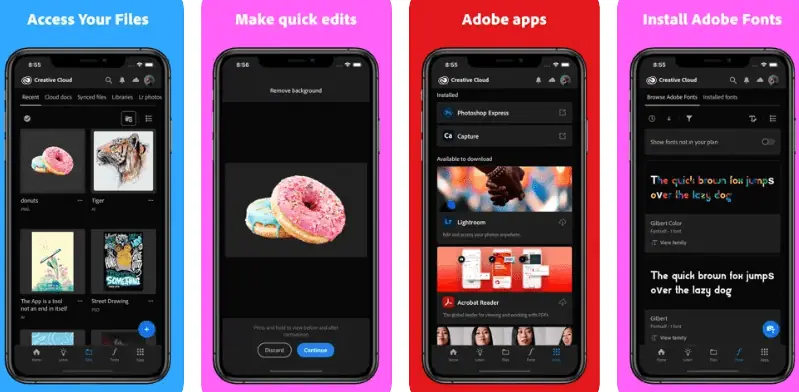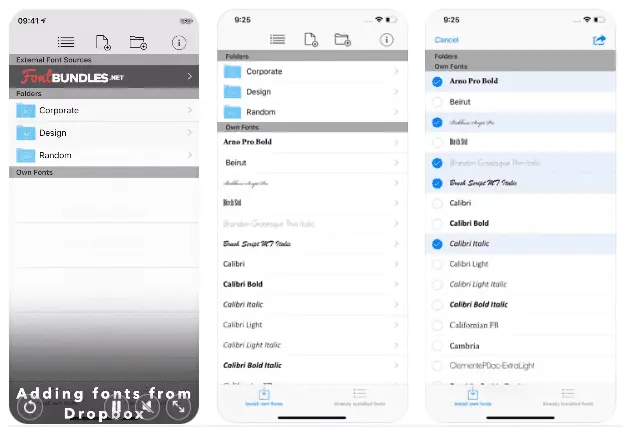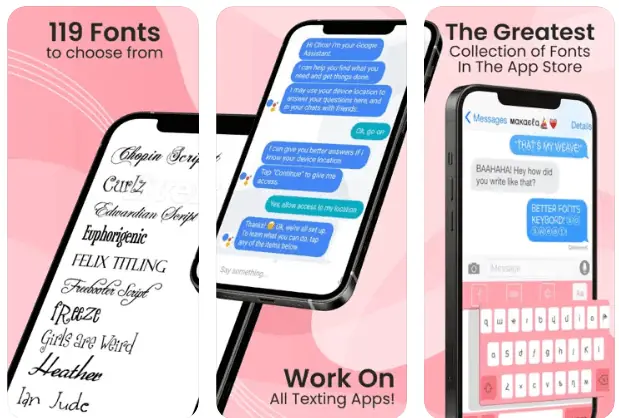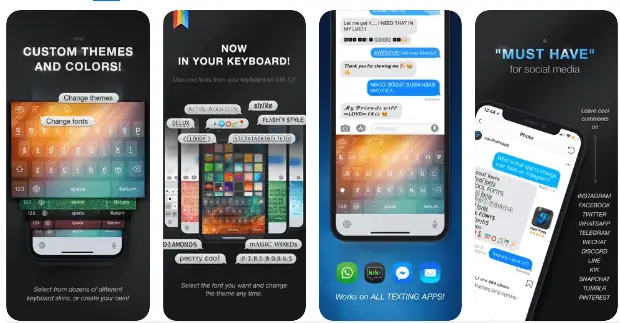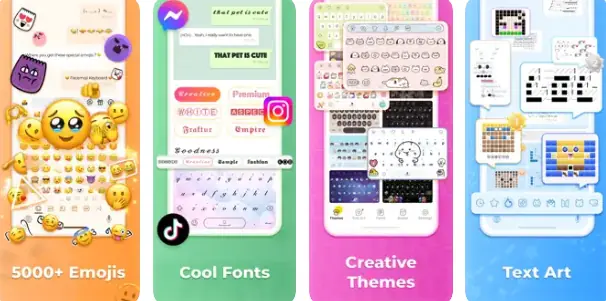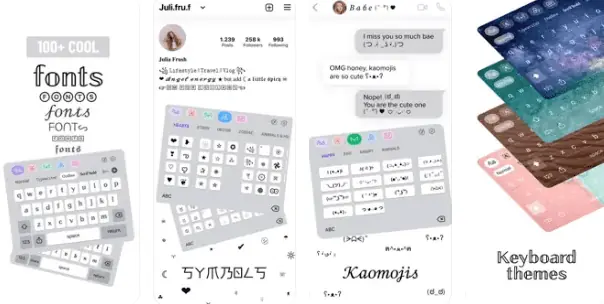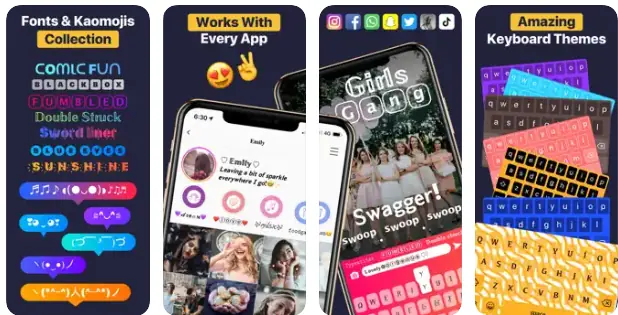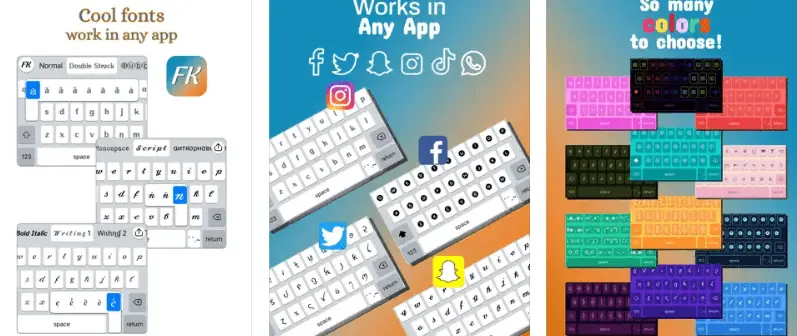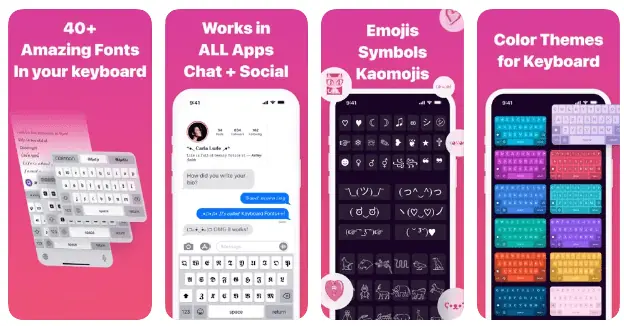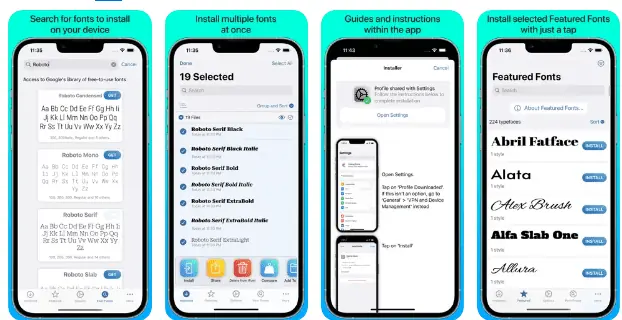
Die individuelle Gestaltung des eigenen Smartphones ist bei vielen sehr beliebt. Daher wollen wir uns einige der besten Apps für Schriftarten ansehen, mit denen du dein iPhone personalisieren kannst.
Viele Blogger haben angemerkt, dass iPhones in Bezug auf Individualisierung nicht ganz mit Android-Geräten mithalten können. Das mag bis zu einem gewissen Punkt stimmen, doch Apple hat stetig nachgebessert und steht dem Konkurrenten inzwischen in nichts nach.
Diese Entwicklung wird deutlich, wenn man sich die Vielzahl an Apps und Widgets im App Store anschaut, die es Nutzern ermöglichen, ihr Smartphone zu personalisieren. Dieser Artikel richtet sich an alle, die ihr Gerät gerne individuell gestalten möchten.
Personalisierung kann viele Aspekte umfassen, wie etwa Automatisierungen, das Hinzufügen von Kurzbefehlen oder Änderungen bei Bildschirmanimationen. Hier soll es um eine kleine, aber wirkungsvolle Anpassung gehen: die Schriftart deines iPhones. Lass uns also keine Zeit verlieren und direkt zu den Apps kommen!
Was sind Schriftarten-Apps?
Bevor wir uns den besten Schriftarten-Apps für iOS widmen, wollen wir kurz definieren, was Schriftarten-Apps eigentlich sind. Im App Store gibt es Millionen von Anwendungen, die unterschiedliche Funktionen erfüllen, und Schriftarten-Apps gehören auch dazu.
Mit Schriftarten-Apps können Nutzer den Stil der Schrift auf ihren Mobilgeräten verändern. Sie bieten eine vielfältige Auswahl an Fonts und Anpassungsmöglichkeiten. Es ist sogar möglich, die Schriftart in einer einzelnen App oder systemweit zu ändern.
Es gibt sowohl kostenlose als auch kostenpflichtige Schriftarten-Apps, wobei Premium-Fonts oft ausgefeiltere und individuellere Anpassungsmöglichkeiten bieten. Viele dieser Apps ermöglichen nicht nur die Veränderung von Größe und Farbe, sondern bieten auch zusätzliche Funktionen wie Texteffekte und Hintergründe.
Schriftarten-Apps können zwar eine unterhaltsame Möglichkeit sein, das Aussehen deines Smartphones zu verändern, aber es ist wichtig zu beachten, dass nicht alle Fonts mit allen Apps und Geräten kompatibel sind. Zudem sind manche Schriftarten möglicherweise nicht optimal in Bezug auf Lesbarkeit und Barrierefreiheit. Daher ist es wichtig, Schriftarten zu wählen, die gut lesbar und benutzerfreundlich sind. Vorsicht ist auch geboten, wenn Schriftarten von Drittanbieter-Webseiten bezogen werden, da diese Schadsoftware und andere Sicherheitsrisiken bergen können.
Warum sollte ich die Standardschriftart auf meinem iPhone ändern?
Wenn es um Schriftarten-Apps geht, stellt sich oft die Frage: Ist es wirklich nötig, die Standardschriftart zu ändern? Die einfache Antwort lautet: Nein.
Die Entscheidung, den Schriftstil und die -größe zu ändern, liegt ganz bei dir. Du hast aber sicher bemerkt, dass die Schriftart das Erscheinungsbild stark beeinflusst, egal ob es sich um ein Dokument, Instagram-Storys oder eine Biografie handelt. Viele verwenden unterschiedliche Schriftarten, um ihre Biografie oder Story attraktiver zu gestalten und hervorzuheben.
Zusammenfassend lässt sich sagen, dass ein Schriftartenwechsel nicht zwingend notwendig ist. Es ist aber dennoch eine Option, die das Erscheinungsbild und die Benutzerfreundlichkeit verbessern kann. Hier sind einige Vorteile, die eine Änderung der Standardschriftart mit sich bringen kann:
Verbesserte Lesbarkeit
Manche Schriftarten sind besser lesbar als andere, besonders für Menschen mit Sehbeeinträchtigungen. Durch die Anpassung der Standardschriftart kannst du eine auswählen, die für dich bequemer und leichter zu lesen ist.
Personalisierung
Eine andere Standardschriftart kann deinem iPhone eine persönliche Note verleihen. Du kannst einen Font wählen, der deinen Stil oder deine Persönlichkeit widerspiegelt oder einfach mal etwas Neues ausprobieren.
Barrierefreiheit
Das Ändern der Schriftart kann die Bedienung für Menschen mit Sehbehinderung oder Legasthenie erleichtern. Einige Schriftarten sind speziell so gestaltet, dass sie mit klareren, größeren Buchstaben und besseren Abständen zwischen Buchstaben und Wörtern leichter zugänglich sind.
Verbesserter Fokus
Manche Schriftarten sind angenehmer für das Auge als andere. Dies kann helfen, Augenbelastung zu reduzieren und deine Konzentrationsfähigkeit zu verbessern. Schriftarten wie Helvetica oder Arial werden oft als beruhigender und angenehmer empfunden als verspielte oder dekorative Schriftarten.
Bessere Produktivität
Eine leichter lesbare und weniger ablenkende Schriftart kann deine Produktivität und Effizienz bei der Nutzung deines iPhones steigern. Sie kann dir helfen, dich besser zu konzentrieren und Aufgaben schneller und genauer zu erledigen.
Zusammenfassend lässt sich sagen, dass eine andere Standardschriftart dir helfen kann, dein Gerät zu personalisieren, die Lesbarkeit und Barrierefreiheit zu verbessern sowie deine Produktivität und Konzentration zu steigern. Bei der großen Auswahl an Schriftarten findest du sicher eine, die deinen Bedürfnissen und Vorlieben entspricht und das gesamte iPhone-Erlebnis verbessert.
Fazit
iOS hat die Anpassbarkeit von Geräten seit jeher kontrolliert. Die Möglichkeit, Schriftarten auf dem iPhone anzupassen, ist für viele Nutzer ein lang gehegter Wunsch. Es gibt Tausende von Apps für Schriftarten. Um dir die Auswahl zu erleichtern, haben wir einige der besten Apps zusammengestellt, die nicht nur die Anzeige deines Telefons verbessern, sondern dir auch bei anderen Aufgaben helfen.